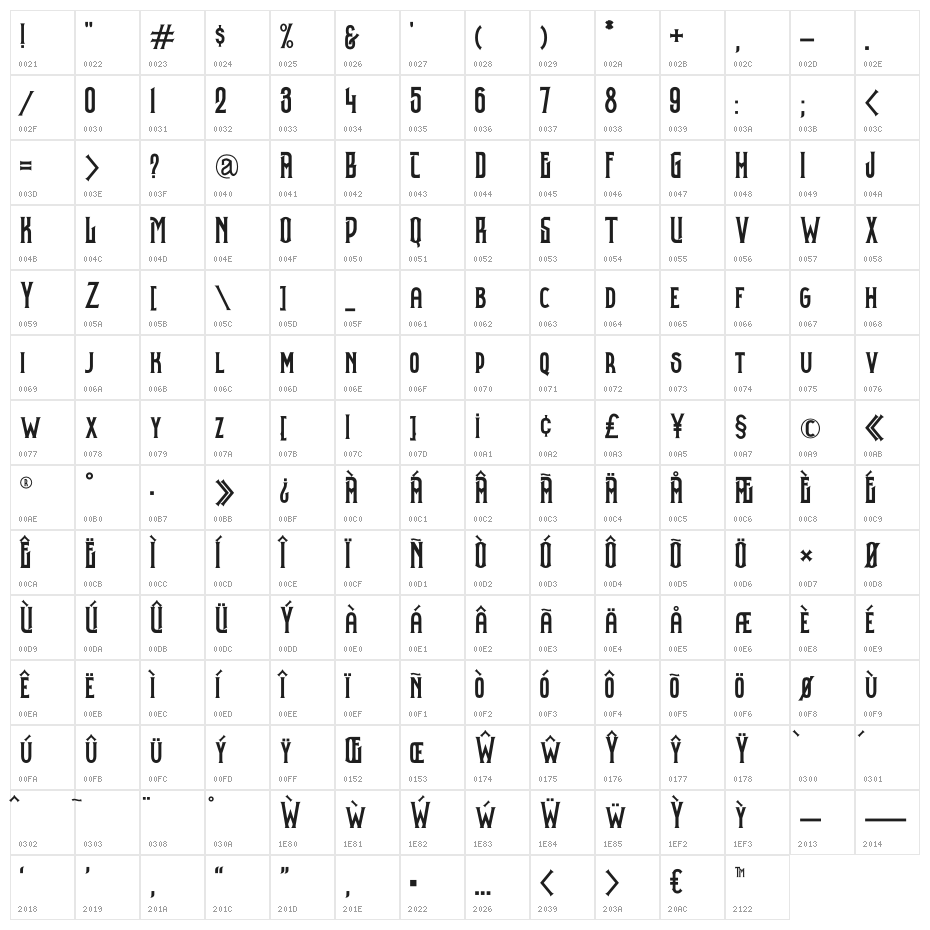
Astaroth Font
| Stile generale | Modern Gothic |
| Progetti proposti | Ideal for projects requiring a dramatic and eye-catching typeface, such as posters, album covers, or branding for edgy or alternative products. |